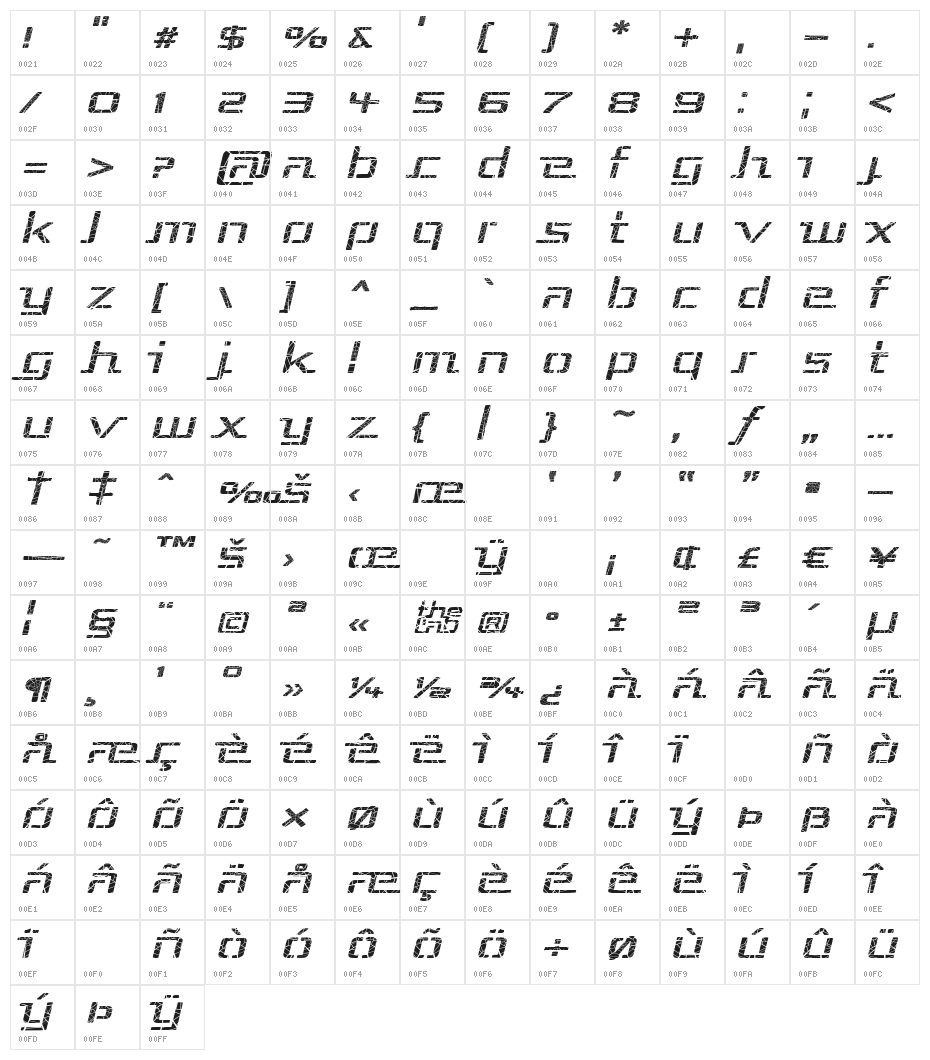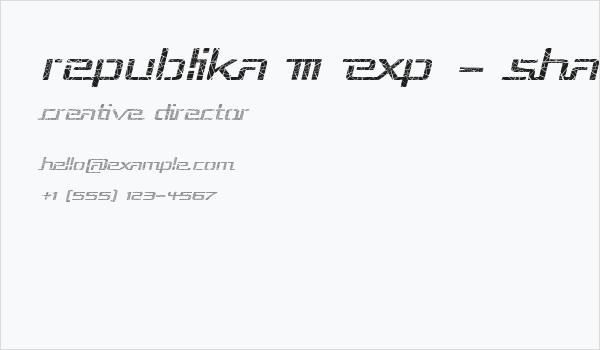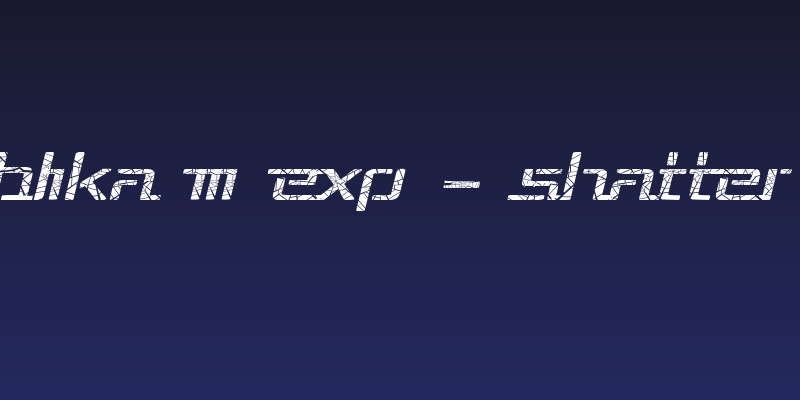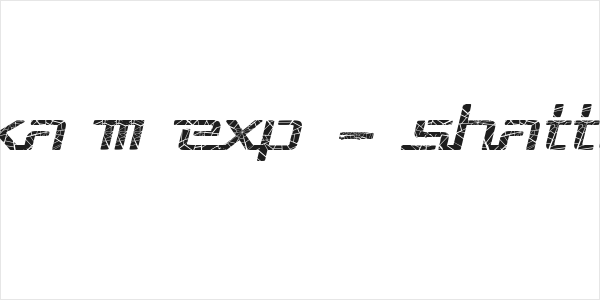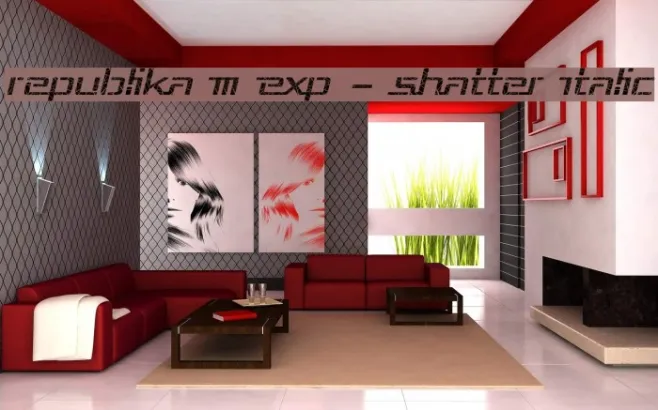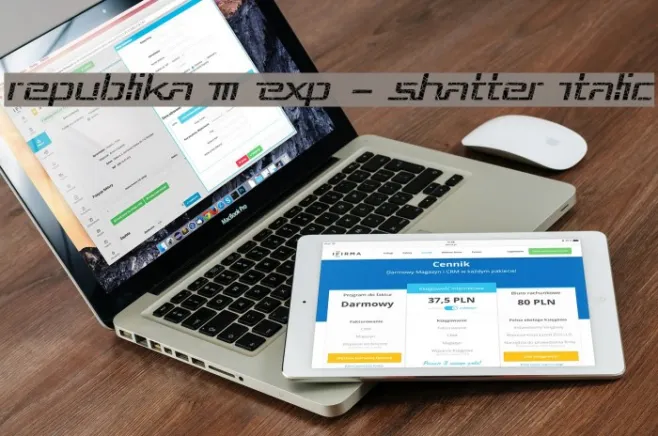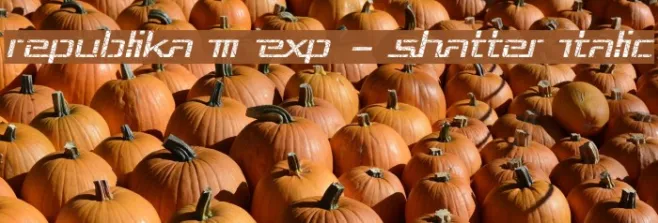
Republika III Exp - Shatter Italic Font
| Progetti proposti | Ideal for album covers, posters, branding for tech companies, and any project needing a futuristic and bold aesthetic. |